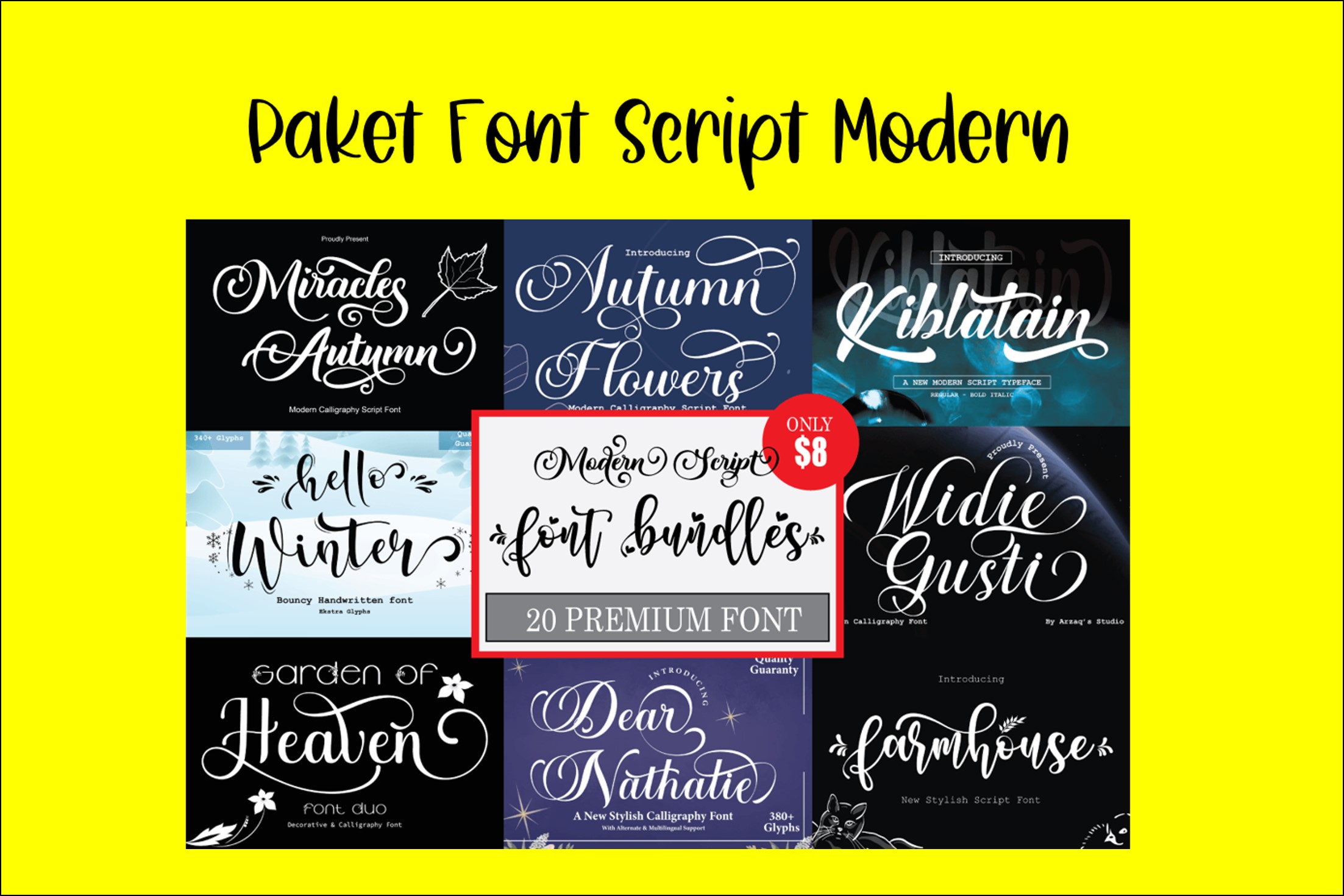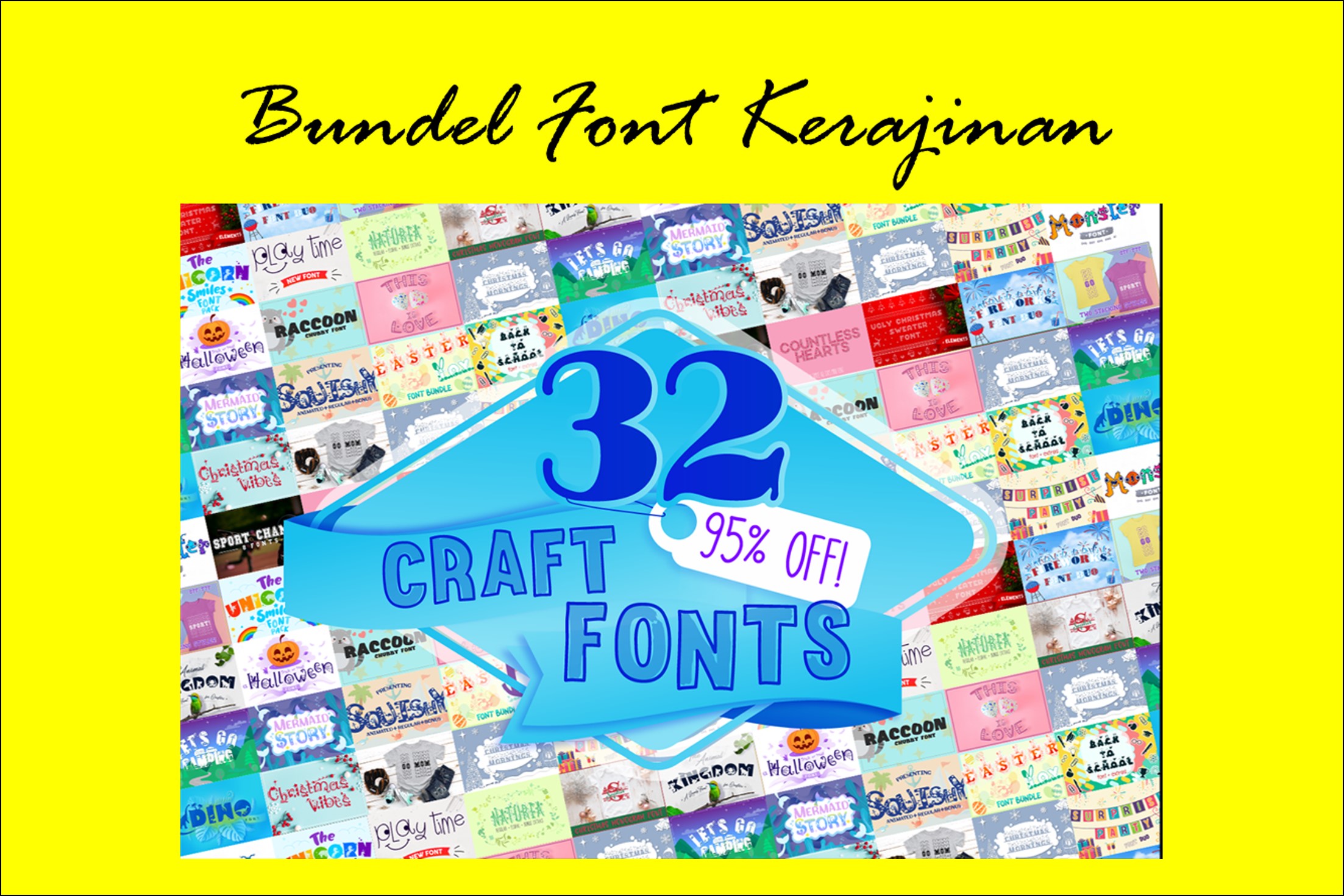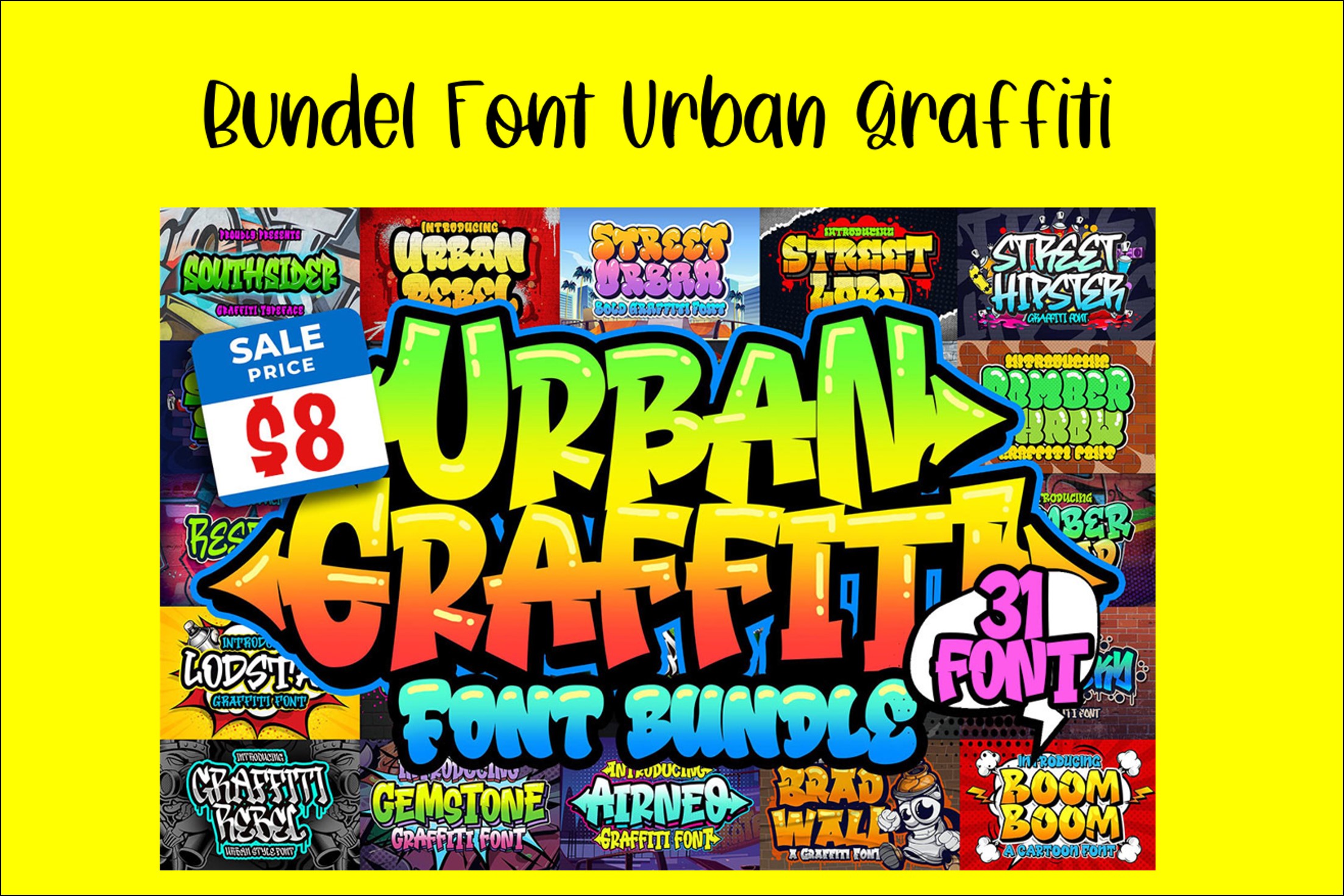
Paket Font Script Modern (20 Fonts)
Bundel ini mengumpulkan 20 font menakjubkan untuk Anda gunakan dalam proyek mendatang.
Bundel Font Kerajinan (32 Fonts)
Bundel Font Kerajinan dengan total 32 font dari 24 jenis font dan Anda pasti akan menyukai masing-masing font. Semua font dalam bundel ini dibuat dari awal, menggunakan poin sesedikit mungkin untuk memastikan Anda mendapatkan hasil terbaik dengan kesulitan minimal.
Bundel Font Urban Graffiti (31 Fonts)
Bundel Font Urban Graffiti mencakup 31 font bergaya grafiti yang menarik untuk Anda gunakan dalam proyek mendatang. Dengan font unik ini, Anda pasti akan membuat desain Anda menonjol!
Bundel ini mengumpulkan 125 font menakjubkan untuk Anda gunakan dalam proyek mendatang. Bagus untuk berbagai keperluan proyek anda
Menghasilkan tipografi yang menarik, indah dan menawan dalam bebagai proyek
Siapapun yang ingin menghasilkan tipografi yang menarik, indah dan menawan dalam bebagai proyek